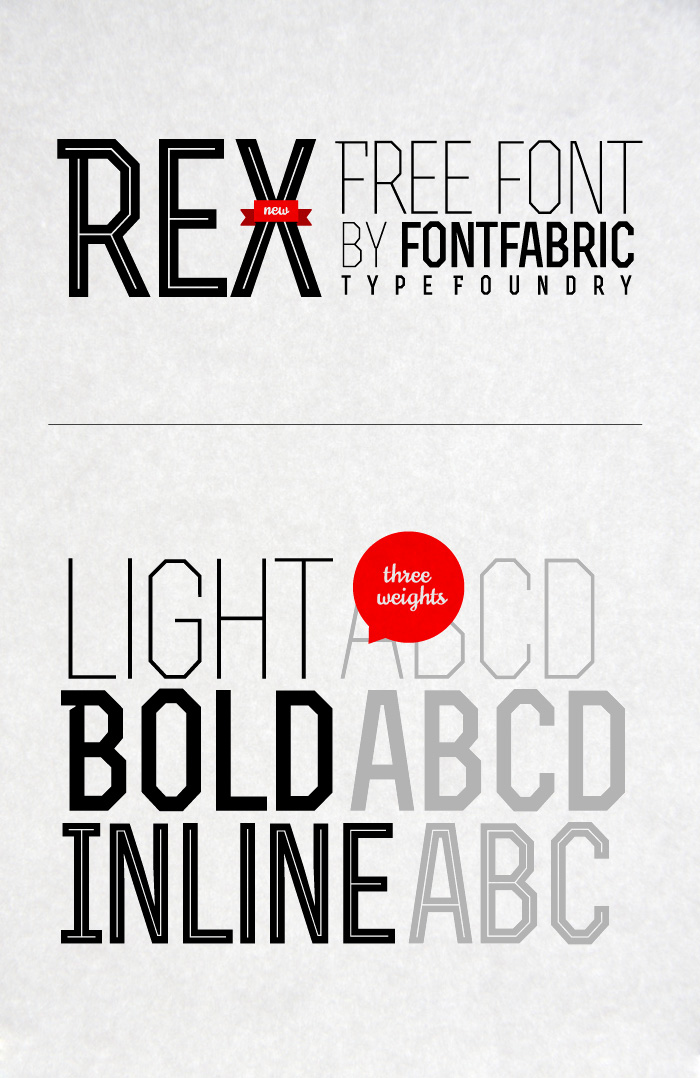
Rex (Fontfabric)
Rex ist ein geradliniger Allcaps-Displayfont. Kommt in Light, Bold und Bold Inline. Dazu auch mit kyrillischer Sprachunterstützung. Beachtet auch die Unterschiede zwischen Versalien und Kapitälchen. Gibt’s gratis bei Fontfabric (Svetoslav Simov).